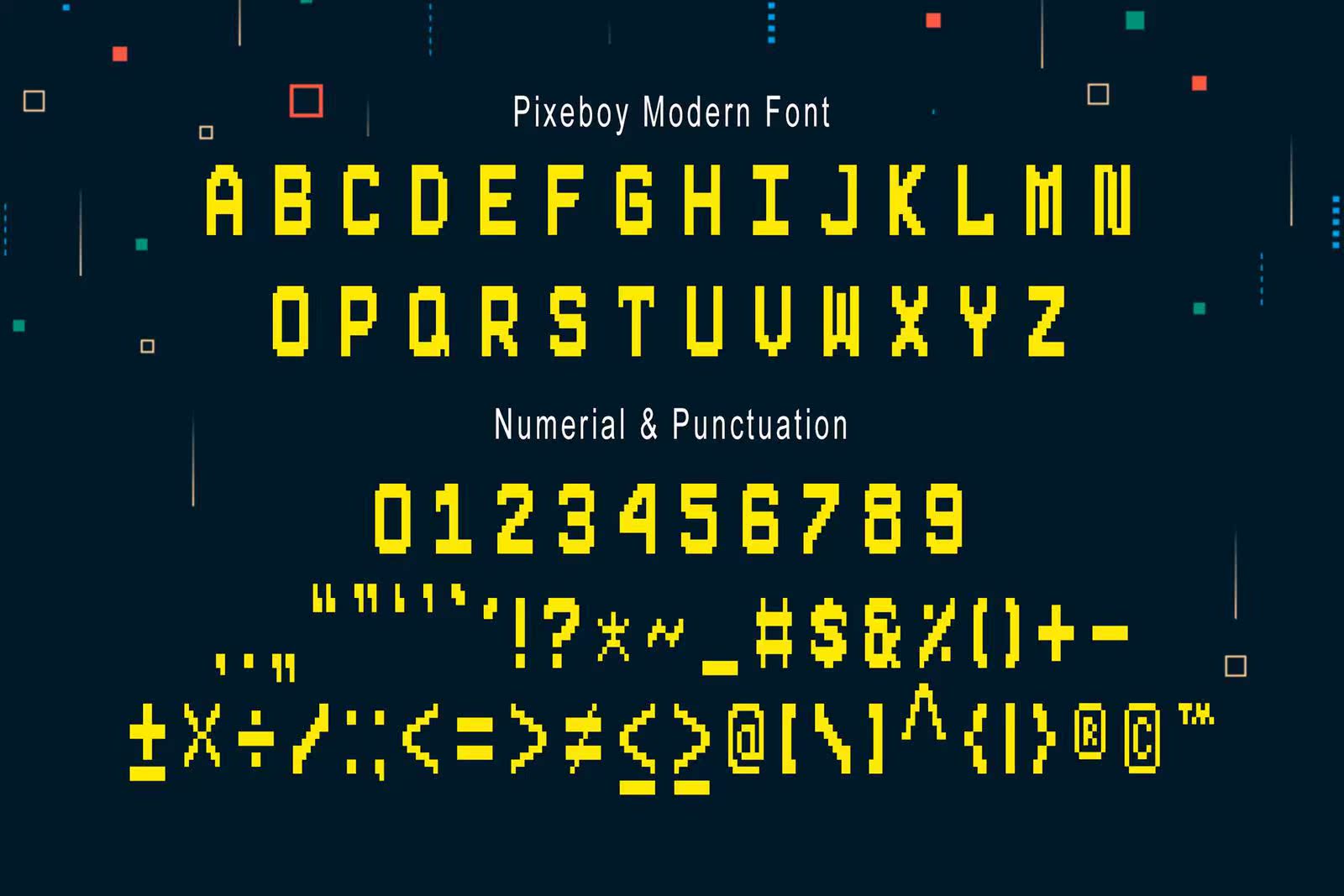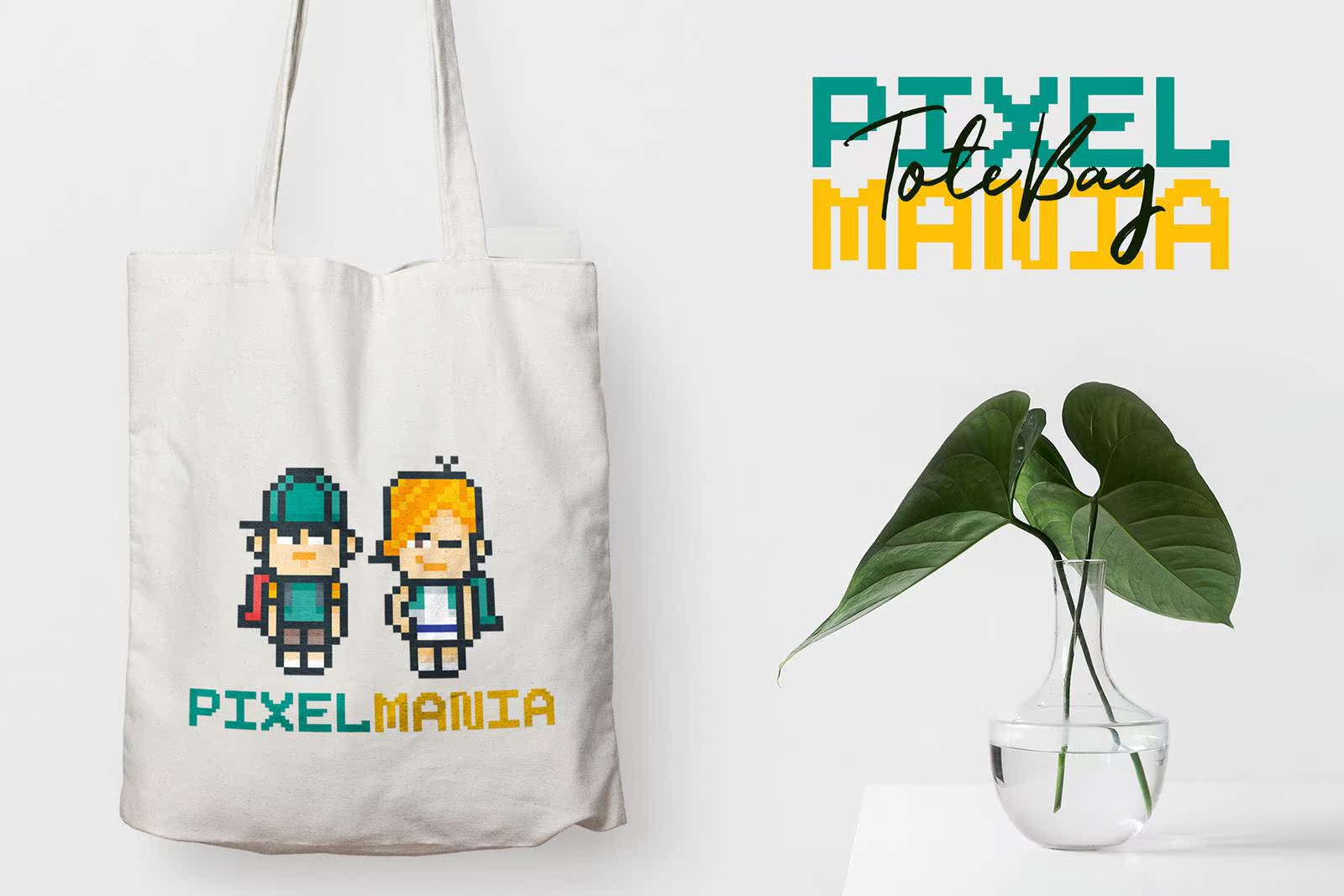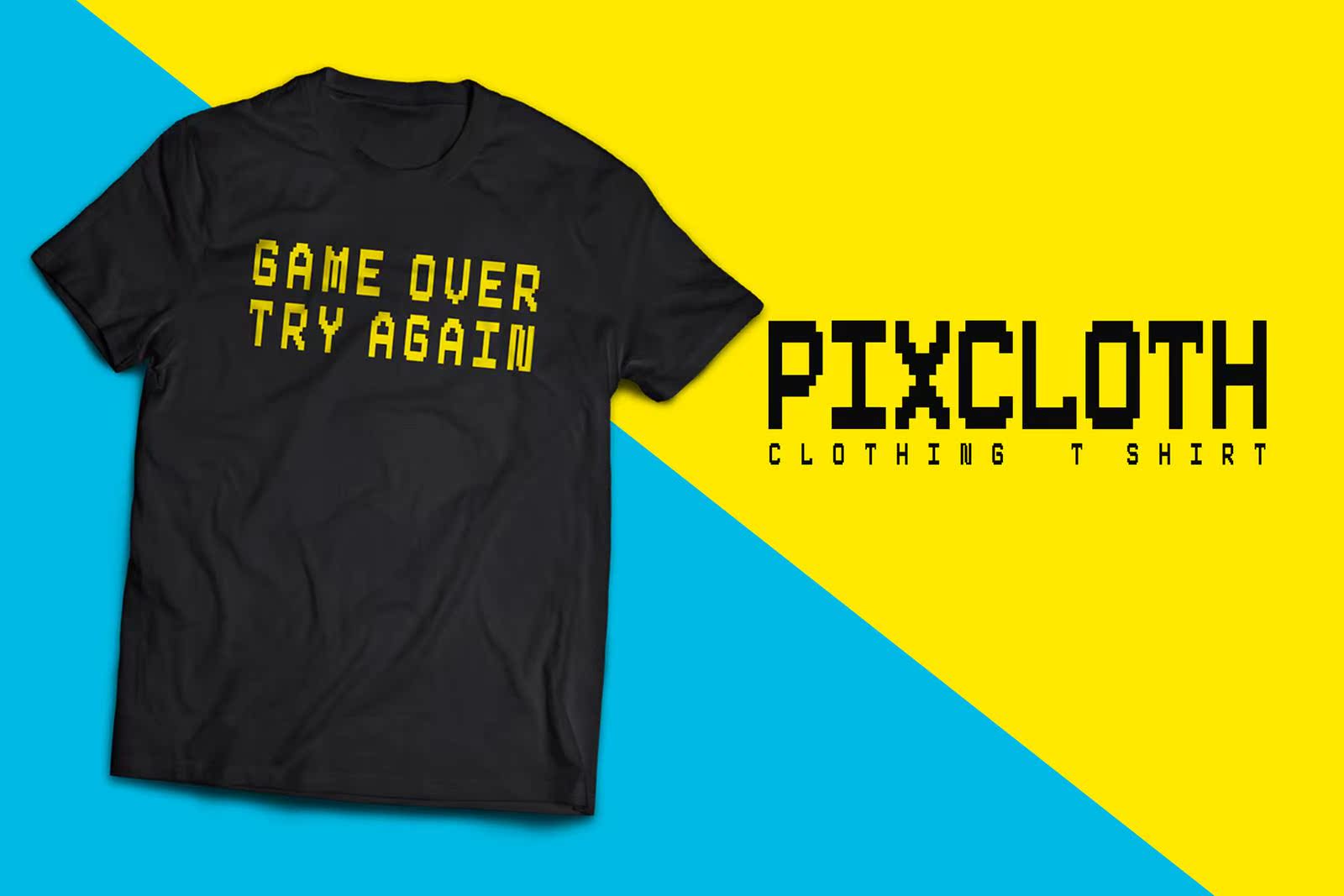
Free PixeBoy Pixel字体是一种现代化且独特的显示字体。它适用于任何类型的显示目的,如徽标、产品包装、海报、merch、品牌等。此PixeBoy是所有Caps中的Pixel样式字体。它选择了80年代的128位游戏机,使其具有同等的技术和静态显示字体,这种自由字体将使任何设计项目脱颖而出。但是,如果您想获得更多功能,请立即购买。